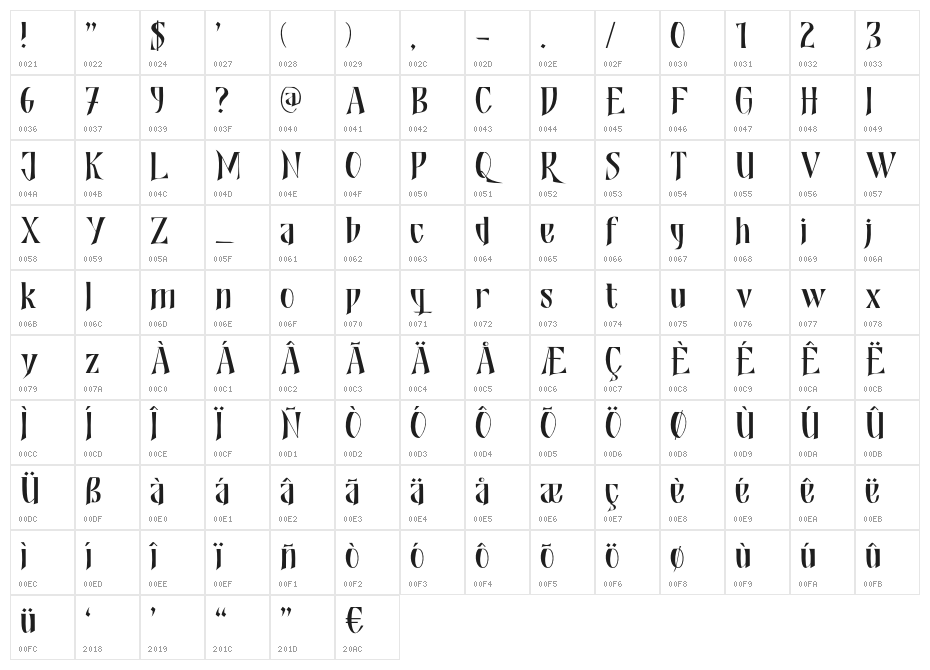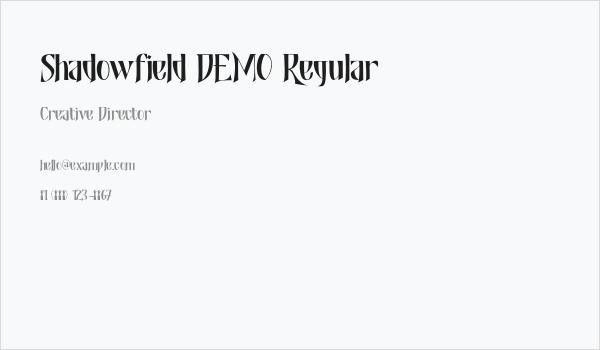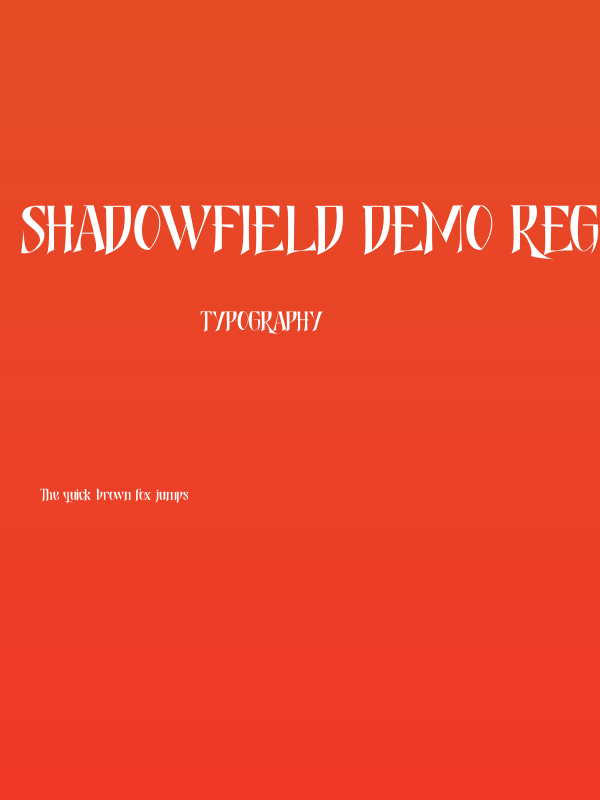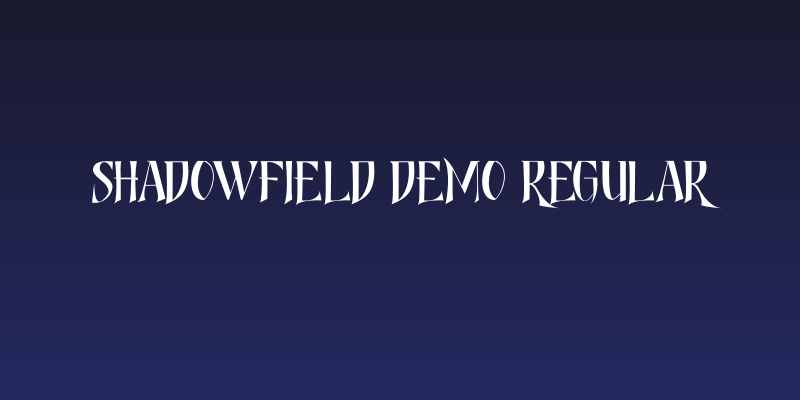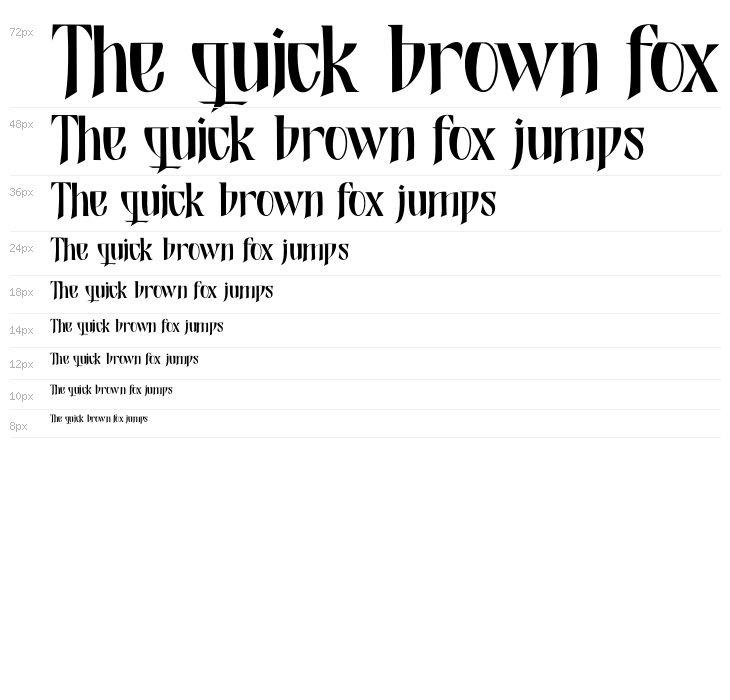
Shadowfield DEMO Regular Font
| Stile generale | Gothic, Dramatic |
| Progetti proposti | Ideal for horror-themed posters, edgy branding, album covers, and theatrical event promotions. |